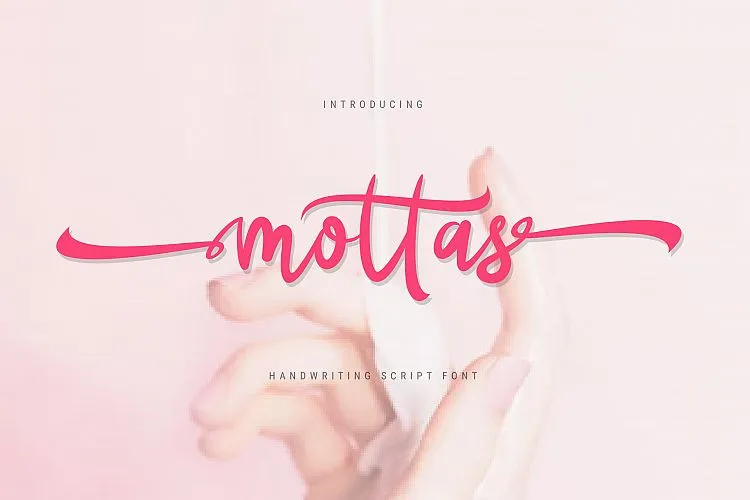
Mottas Script Font – Download Grátis
Esta é uma fonte script escrita à mão que apresenta um estilo urbano autêntico, com elementos inspirados em esportes extremos. Ela foi desenvolvida pelo designer 0001themes e tem uma combinação única de street style e calligrafia artística, criando caracteres decorativos e uma base de texto que dança ao seu redor. Prestigiante apresentamos a Mottas Font! Esta fonte Script Mottas é um estilo novo e moderno, com um ar refinado e elegante. Ela brilha em diferentes tipos de materiais como cartões de convite, materiais de marca, cartões de visita, declarações, fitas informativas e mais! Seja para eventos especiais ou projetos pessoais, essa fonte é perfeita para dar um toque sofisticado aos seus designs.